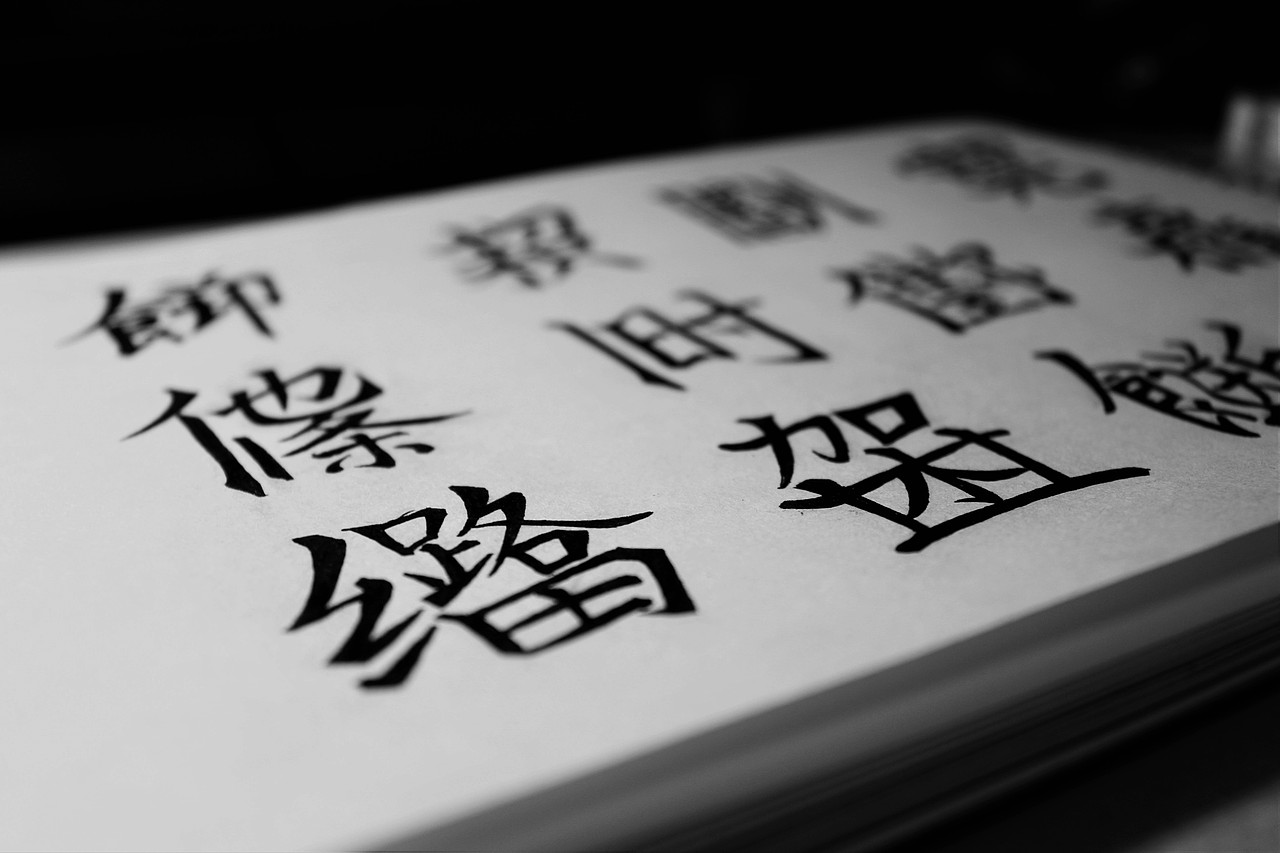
之前围绕着广州这个主题做的字体设计,每一篇都用一种设计方法和表现方法做的,第一篇是以图案为元素做的字体设计;第二篇是以广州的历史和文化为主要调性,以及篆刻印章的表现手法做的字体设计;本篇目我主要用了粤语的元素结合共用的表现手法,进行字体设计。
粤语是一个很庞大且复杂具有长远历史的语言系统,粤语的字体对应其发音,具有浓厚的广府味。所以我将我们平常所用到,所讲到的粤语词组组合成一个字体。这个过程还是很有趣的。
这是一些手稿,是不是看不懂?哈哈哈哈哈哈......
在电脑上进行调整,从左到右为“细路”,“得戚”,“挂住你”,“招积”,“架世”,“他条”,“平靓正”,“话口未完”,至于什么意思,问问百度就知道了,哈哈哈哈......